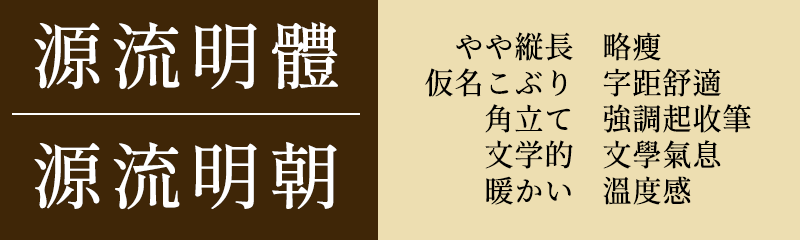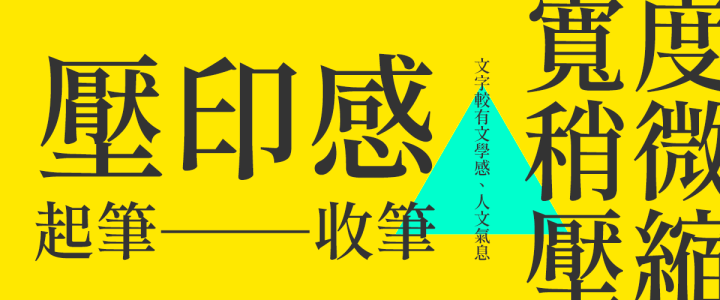
源流明体「源流明體」「源流明朝」下载
台湾最活跃的字型社团「字嗨」管理员 But Ko ,释出三款改造自思源宋体的繁体中文字体,开放给需要的使用者免费下载!
汉字宽度稍微压缩,显得比原始的思源宋体要稍微瘦长。 并且在横笔的起笔与竖笔的起笔、收笔处,全都加上粗细变化。 彷彿重现铅字的压印感,文字较有文学感、人文气息。